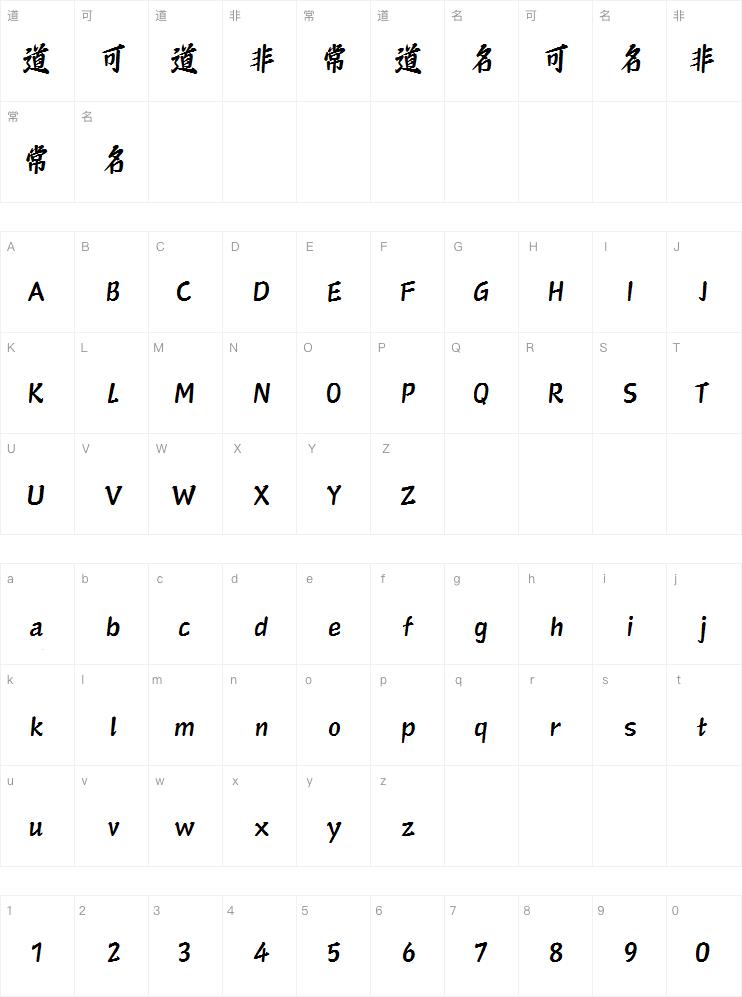
山海时光脉冲,是一款全新的字体,包含汉字9169个,符号200+个。该字体字形灵动多变,笔画以25度角向右上方倾斜,在灵动的同时而又极富速度感。在粗细的纵横间,拥有非常规的自由灵动特性。笔画间的关系密不可分,同时也增加了字体的自由洒脱之感。结构多变灵动,字形活泼清新,造型生动有趣,具有灵活的适用性,天真俏皮又不失时尚感。字形比例按照宽高4:5的比例设计,使得字体显高;同时笔画带有翘角装饰,使得字形带有律动感;25度角向右上方倾斜的设计,使得字形带有速度感,带来强有力的视觉冲击效果。该字体在流动的美感的同时,又有着律动的速度感,在正式用字场合落落大方,在日常使用环境中不失亲切友好,能够更能适应当下时尚潮流的需要,助力各大新产品夺取标题主战场。